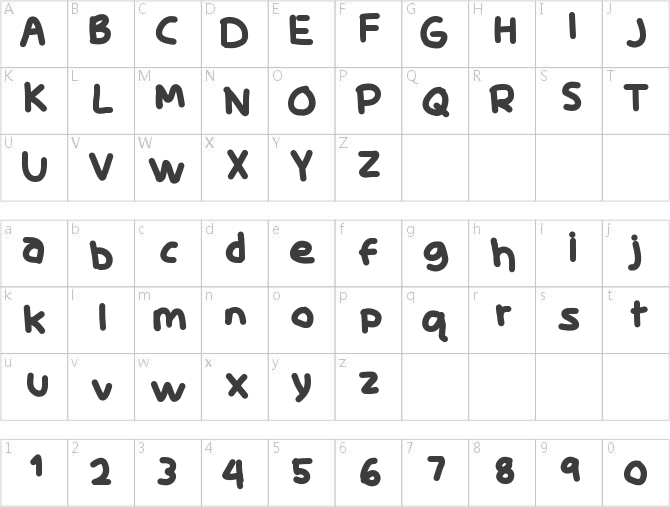
字体名称: SkidooF
SkidooFat_RH
SkidooFat_RH介绍
SkidooFat_RH字体字库是一款让人赏心悦目、百看不厌的英文字体,适合各类广告和产品包装设计应用,字体大小0.03MB,格式为ttf字体,上传用户是小猴子1003,作者/版权方为未知
SkidooFat_RH效果图